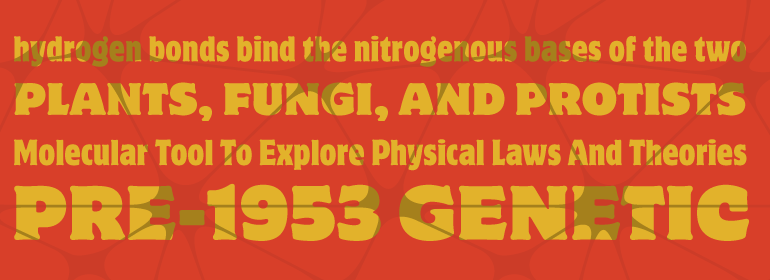
ITC Motter Corpus™
ITC Motter Corpus™,这款字体结构工整、笔画清晰,兼顾美观与易读性,适用于标题、正文、海报、包装、LOGO 等多种场景。字形优雅稳定,风格百搭耐看,适配日常排版与创意设计,让文字呈现更舒适、更具质感。ITC Motter Corpus™一笔一画,皆是细节,以均衡的比例、流畅的线条打造舒适视觉体验,字形端正大气,风格简约现代。无论是商业设计、品牌宣传还是日常排版,都能轻松驾驭,让文字更有格调与力量。ITC Motter Corpus™字体下载。
字体品牌: ITC(Monotype) 设计师:Motter,Othmar 字体分类:衬线体 字体属性:外文 字符集:Unicode 发布时间: 2018